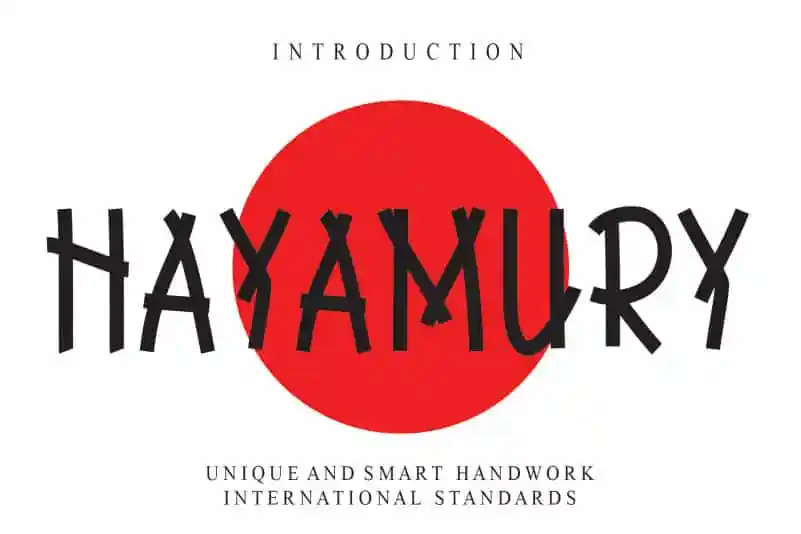
HAYAMURY Display Font
A HAYAMURY Display Font é uma fonte para decoração especial criada pelo designer creativeletter, oferecendo uma experiência única e memorável aos usadores. Este tipo de letra tem um charme singular que vai dar vida à sua marca ou ao seu próximo projeto gráfico. Com linhas delicadas e formações emolduradas, HAYAMURY é perfeito para aplicar em logotipos, materiais de merchandising ou até mesmo em arquitetura interno. Combinando elementos artísticos com uma leveza elegante, a HAYAMURY se destaca como uma fonte exuberante que pode transformar simples texto em obras de arte. Suas linhas suaves e as formas delicadas formam um padrão perfeito para quem deseja dar vida ao design no nível mais alto. Este tipo de letra é uma escolha ideal para aqueles que querem criar um impacto visual impressionante, deixando um sabor agradável em qualquer espaço onde for aplicada.